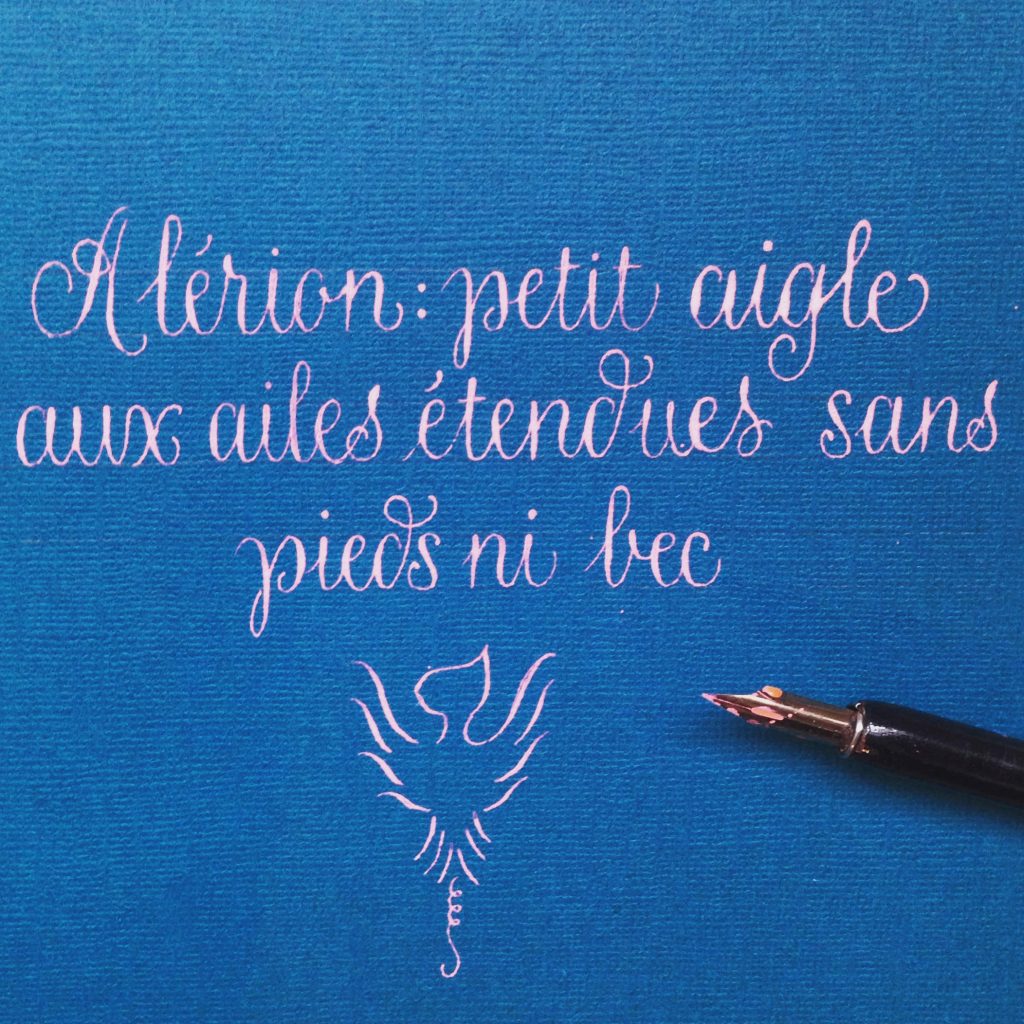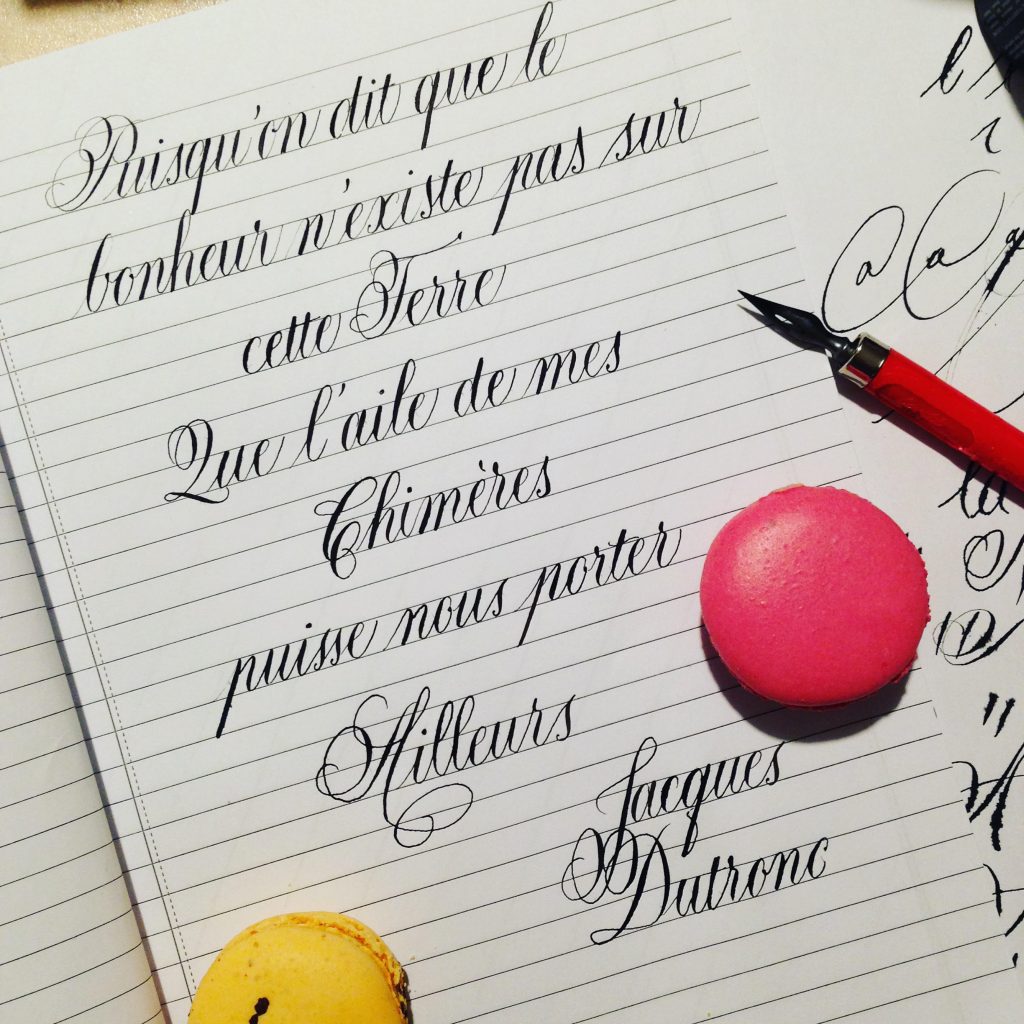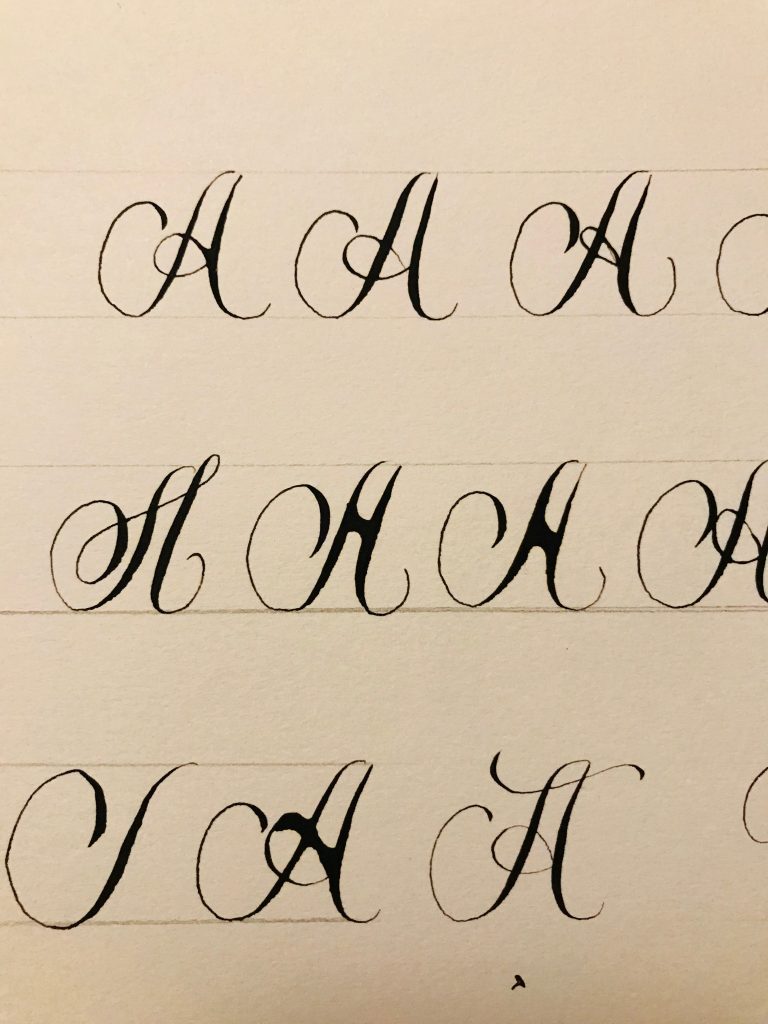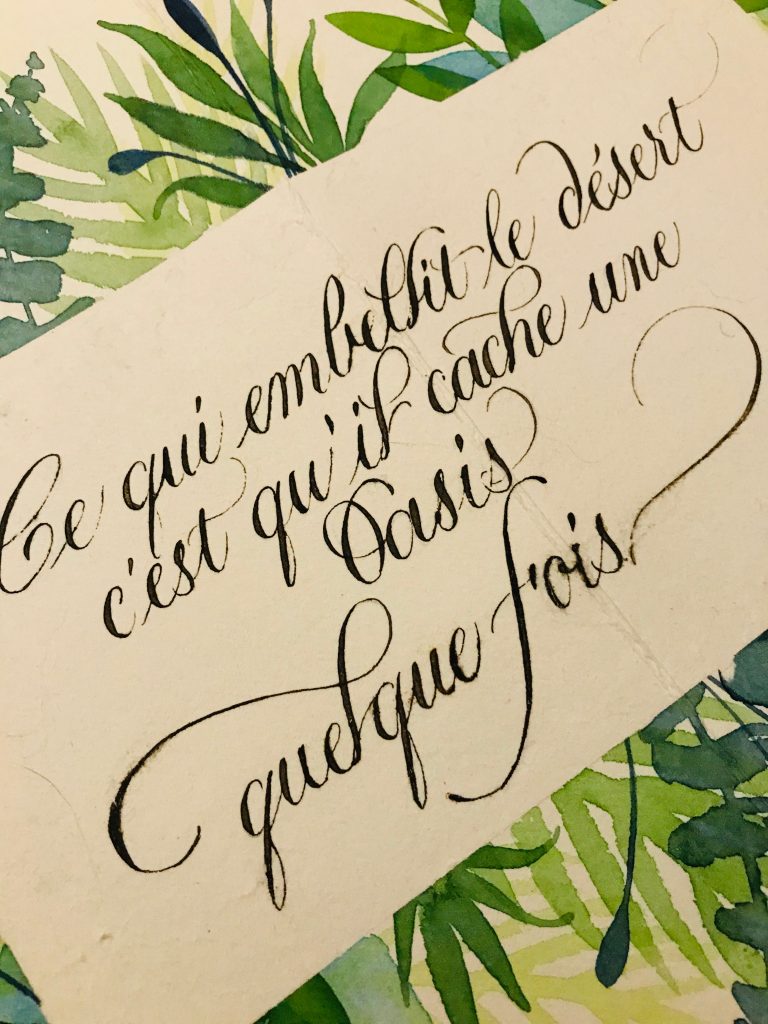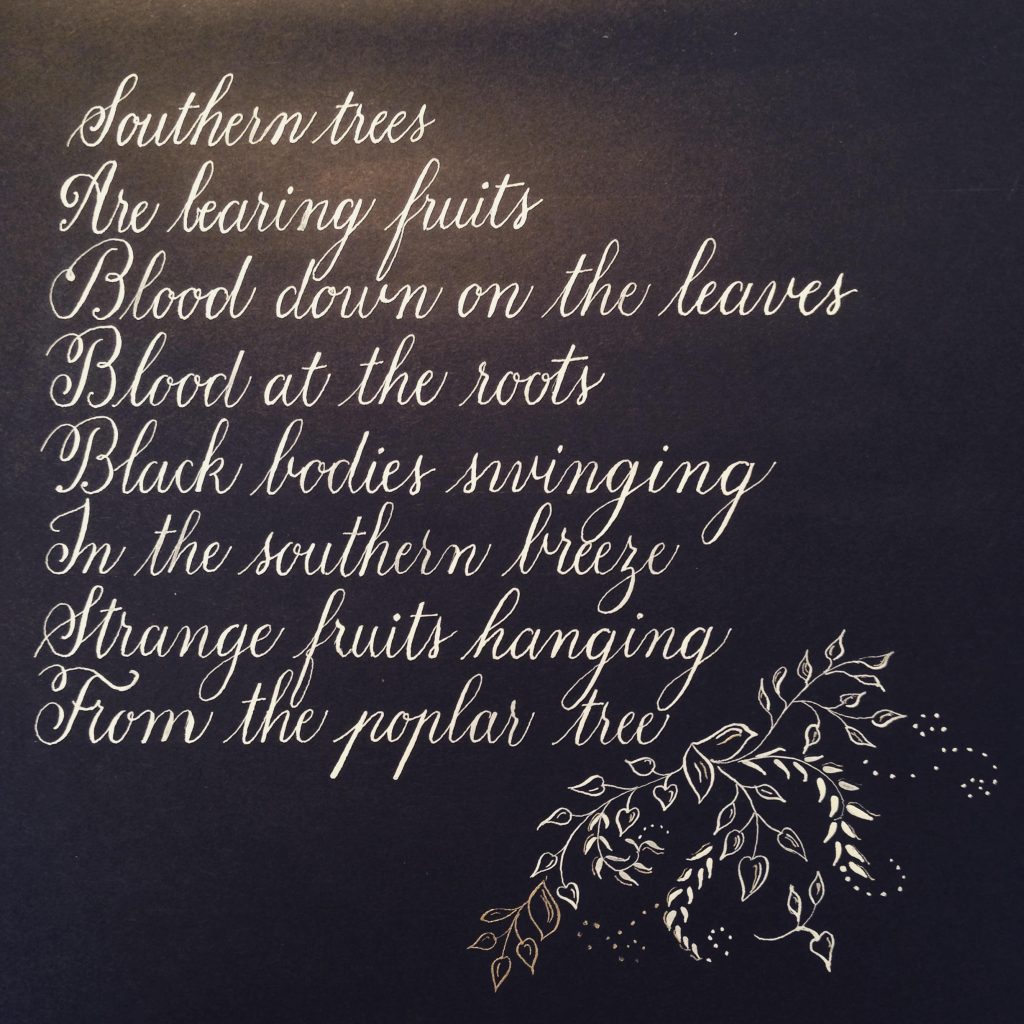
Parfois, suivre des instructions dans des livres et travailler consciencieusement ne suffit pas à atteindre la belle écriture tant espérée. Pourtant vos efforts et votre motivation sont au top, mais il se passe des choses, des petits désagréments ou des accidents auxquels vous ne voyez pas de solution.
Je suis passée par là aussi, et cela m’arrive encore. La différence, c’est qu’avec un peu d’expérience j’arrive à mieux identifier d’où vient le problème, et éventuellement, j’ai des pistes de solutions.
Cet article est là pour évoquer des problèmes courants que l’on rencontre en apprenant la calligraphie. Il concerne principalement la plume pointue (donc l’Anglaise ou Copperplate), et les pistes proposées peuvent éventuellement s’appliquer aux écritures à la plume large.
L’encre coule trop vite et fait des pâtés/gouttes sur la feuille
Normalement l’encre, même si elle est bien fluide, ne doit pas couler « trop vite ». Si c’est le cas, il peut y avoir plusieurs explications :
1. Vous tenez votre plume trop verticale : essayez de la tenir plus inclinée par rapport à votre feuille
2. La plume est neuve, l’encre perle dessus : il faut la nettoyer à l’eau tiède et au savon, puis bien l’essuyer, avant de s’en servir.
3. Si votre plume est bien nettoyée et que l’encre ne semble pas « accrocher » dessus, sucez-la, tout simplement (si elle est propre bien sûr !). La salive agit comme du fiel de bœuf, dégraisse la plume et permet une meilleure adhérence de l’encre. J’ai déjà donné quelques explication dans un article précédent.
4. L’encre est trop liquide : ceci arrive parfois avec les encres aquarelle comme les Ecoline ou les Colorex. Quelques gouttes de gomme arabique améliorent la viscosité de l’encre et son adhérence sur la plume
Ma plume accroche le papier
Un papier qui accroche et qui fuse : ratage assuré si on maîtrise mal l’écriture. Optez pour des papiers lisses, moins risqués pour les débutants
1. Comme expliqué ci-dessus, c’est sans doute que vous tenez votre plume trop verticale. Essayez de l’incliner davantage.
2. Votre papier n’est pas assez lisse. Attention aux papiers à grain, notamment au papier aquarelle. Si vous débutez, cantonnez-vous à des supports à grain très fin/satiné, comme le bloc Rhodia blanc (qui existe en non ligné, ou quadrillé).
3. Vous mettez trop de pression dans les ascendantes : rappelez-vous, le trait doit être ultra léger, presque invisible, comme si la plume survolait le papier.
4. Changez de plume : certaines plumes ne sont pas de bonnes amies. Si elles conviennent à certains, il se peut tout à fait qu’elle ne vous convienne pas à vous. Pour débuter, essayez par exemple la Nikko G.
5. Vous êtes trop tendu-e : voir ci-dessous
Mes lettres sont saccadées, elles manquent de rondeur
Vous êtes probablement trop tendu-e. Détendez-vous, et revoyez votre installation :
• Vous êtes perpendiculaire à votre feuille : même si votre feuille est inclinée, vos épaules sont bien perpendiculaires à l’axe de la feuille
• Rien n’encombre l’espace de votre bras droit, qui peut se mouvoir sans contrainte. Il faut vraiment qu’il n’y ait rien !
• Respirez en profondeur : une grande respiration complète avant de commencer une lettre. Puis une inspiration dans les ascendantes, une expiration dans les descendantes. Essayez de garder ce rythme de respiration : on a tendance à retenir son souffle pour ne pas trembler. En fait, en bloquant la respiration, on coupe la fluidité du geste et on a du mal à finir la lettre.
Raide, saccadé, maladroit : c’est normal lorsqu’on débute
Enfin, la juste rondeur s’acquière avec la pratique. Il est normal que les lettres soient un peu raides lorsqu’on débute. Il y a tellement de sources de crispation : la nouveauté, un outil qu’on ne maîtrise pas, etc. Pour acquérir cette souplesse, j’ai d’abord travaillé avec une écriture droite, plutôt qu’une écriture inclinée. Cela m’a permis de prendre possession de la plume, d’être « mentalement disposée à la rondeur et à la générosité de la lettre », quitte à exagérer un peu. Une fois à l’aise, je suis passée à l’écriture anglaise inclinée.
Pourquoi ne pas vaincre ses appréhensions en commençant par une écriture droite, ronde et généreuse ?
Autre bonne pratique : travailler sur un grand module. En français, cela veut dire travailler avec une hauteur de lettre de 1 cm. Cela vous parait grand ? Exact, mais cela vous aidera à travailler avec une bonne amplitude, notamment pour maîtriser les pleins et les déliés. Il est difficile de bien moduler sur 0,5 cm : alors voyez grand !
Mes lettres sont toutes tremblottantes
La tremblotte peut être causée par la nervosité, l’appréhension, une mauvaise posture ou un souci neurologique/souci de santé. Dans le quatrième cas, je ne suis pas en mesure – bien sûr – de vous conseiller.Pour les trois autres :
1. Évitez, évidemment, les excitants tels que thé, café, tabac, boissons énergisantes…
2. Respirez en profondeur avant de vous mettre au travail